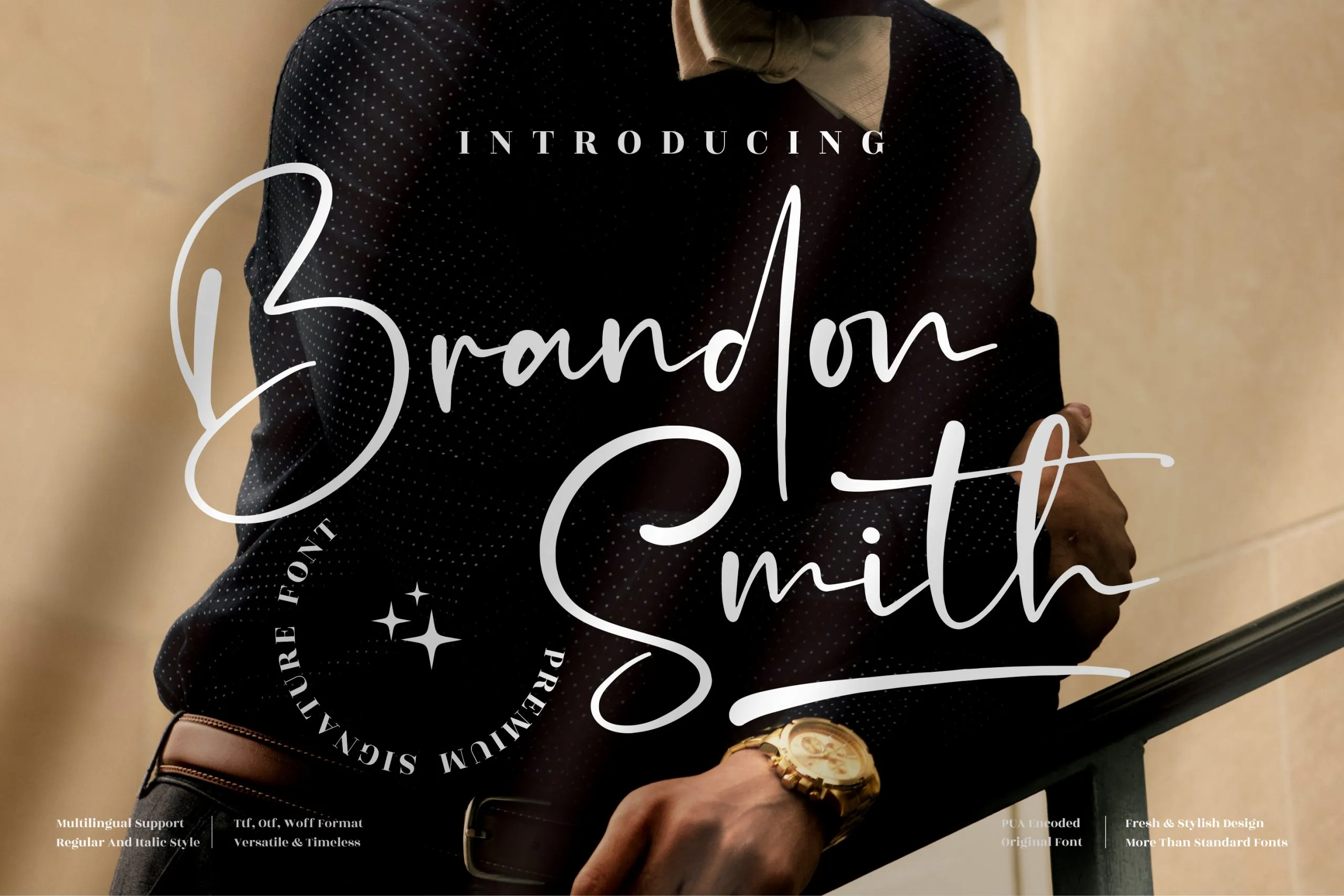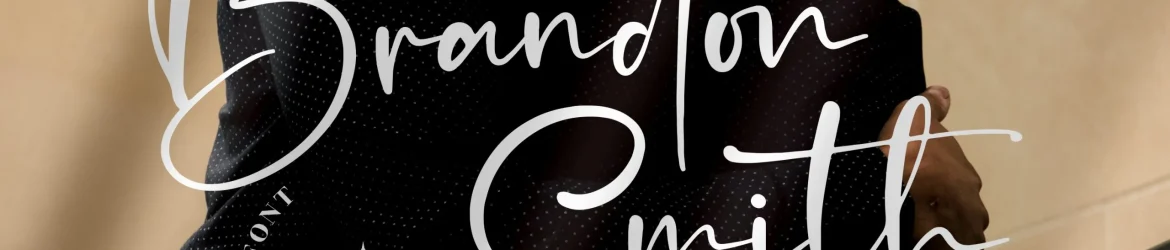
A fonte ‘Brandon Smith Font’, criada pelo designer perspectype, é uma escolha perfeita para projetos que exigem um toque elegante e personalizado. Esta singular fonte escrita a mão é ideal para aplicações como logotipos, projetos de marca, designs de móveis de casa, embalagens de produtos, tênis de mug, bilhetes de cartão de crédito, convites de casamento, encomendas, etiquetas, fotografia e até mesmo marcadores para eventos especiais. Ideal tanto para as mais simples como as mais elaboradas criações visuais, a ‘Brandon Smith Font’ oferece um toque sofisticado que transmite confiança e individualidade aos seus projetos. Seja você um designer de logotipos ou uma marca querendo dar sua identidade um pouco mais personalizado, esta fonte escrita a mão é perfeita para atender às suas necessidades. Sempre garantindo um acabamento de alta qualidade que faz toda a diferença em qualquer projeto.